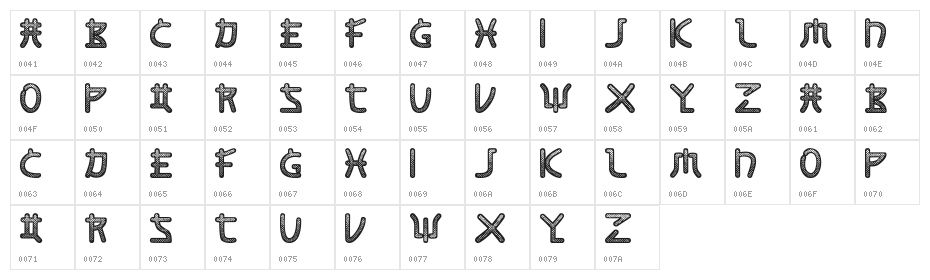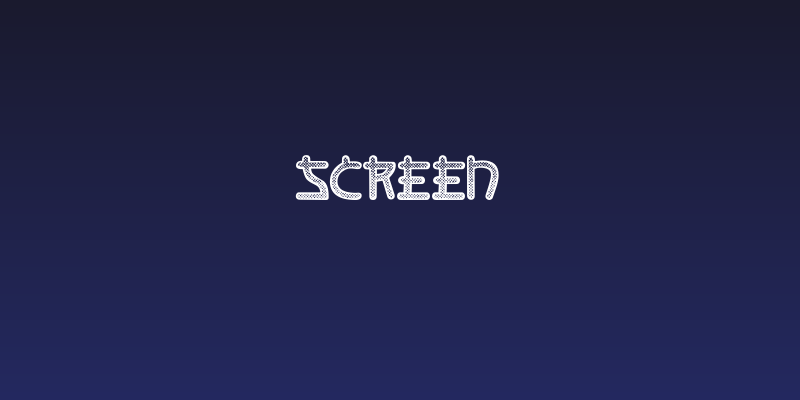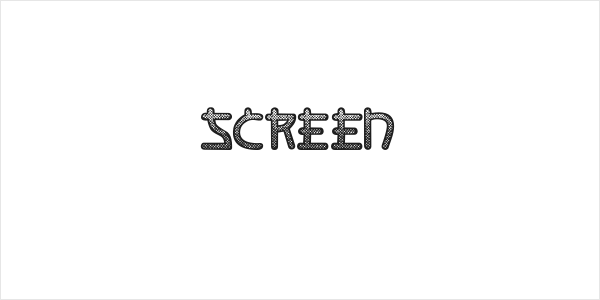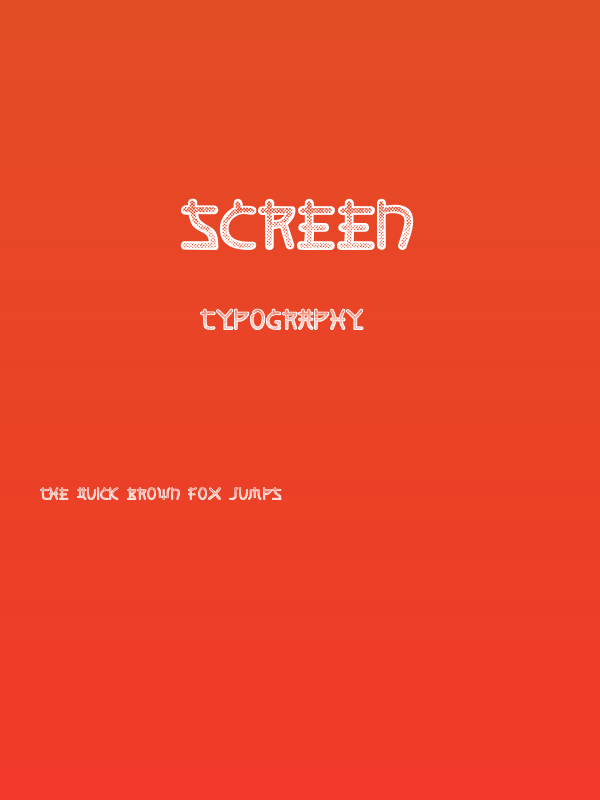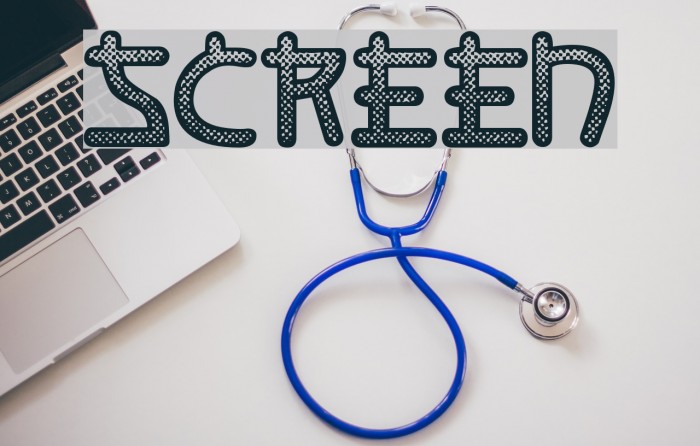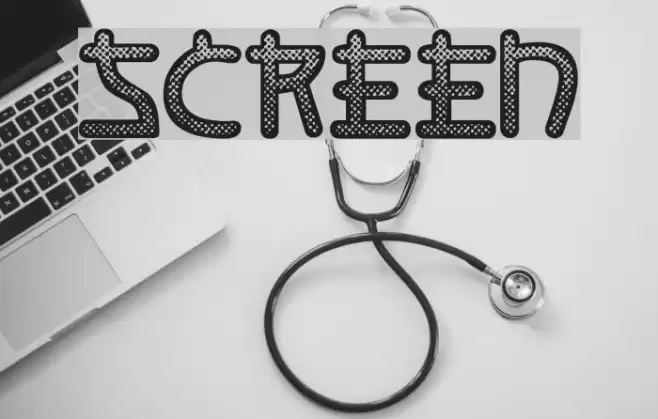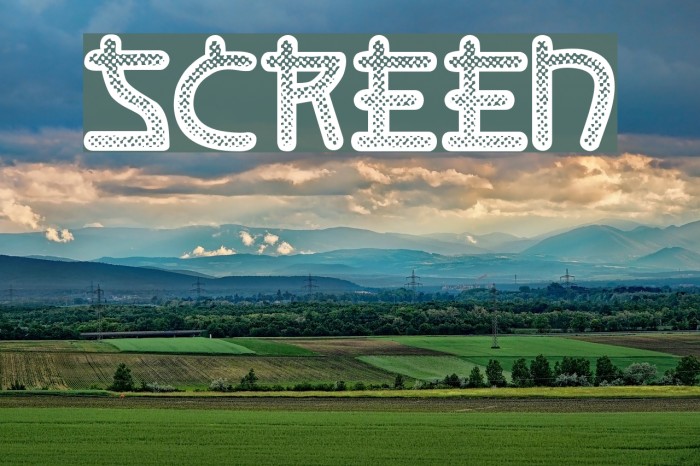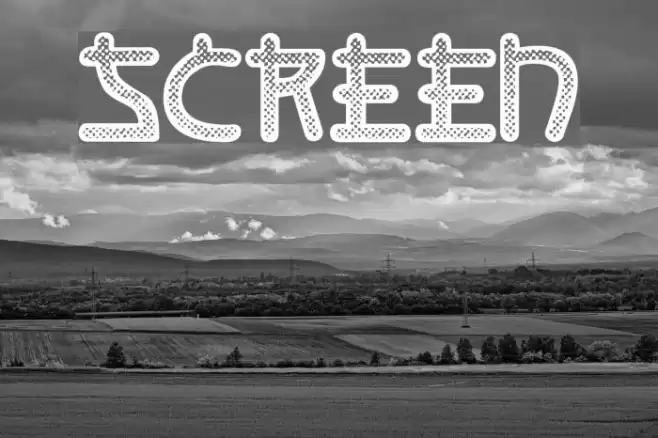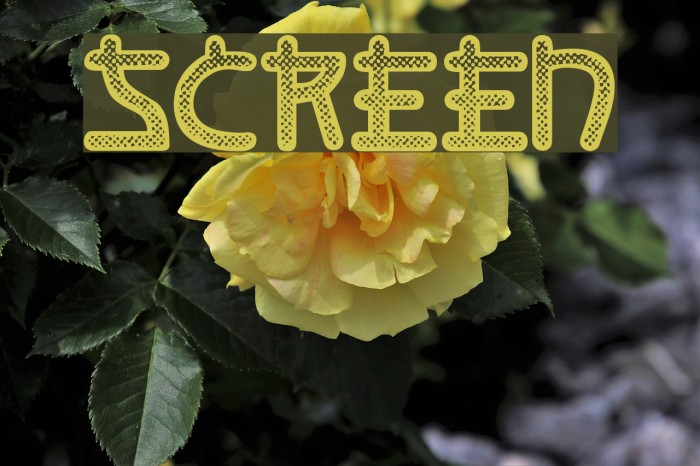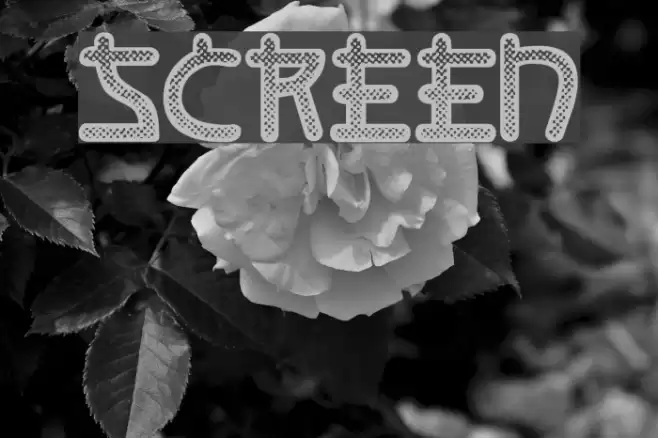
Screen Font
| Estilo general | Playful, Whimsical, Decorative |
| Proyectos propuestos | Ideal for children's book covers, playful branding, party invitations, and creative posters. |